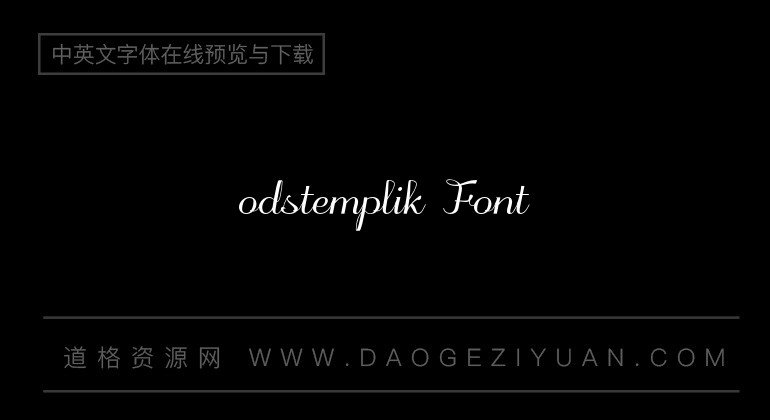
odstemplik Font
odstemplik Font 是一种免费的字体,它的设计旨在提供一个现代而有趣的外观,同时保持易于阅读的清晰性。 这种字体的设计重点在于字母的形状和线条的粗细,每个字母都有自己的个性和独特的特征,使得它们在大多数情况下都非常易于区分。它的线条较为粗细,使得字体在小字号时也能够保持清晰的可读性。 odstemplik Font 适用于许多设计项目,如海报、宣传单、标志、包装设计等等。通过这种字体,你可以轻松地创建一个现代、有趣、易于识别的设计。
odstemplik Font是一款非常不错的手写艺术字体,具有很好的视觉感,适合于文化类的宣传设计、商业类品牌的广告和产品包装设计以及个性化文字排版等较多场景。